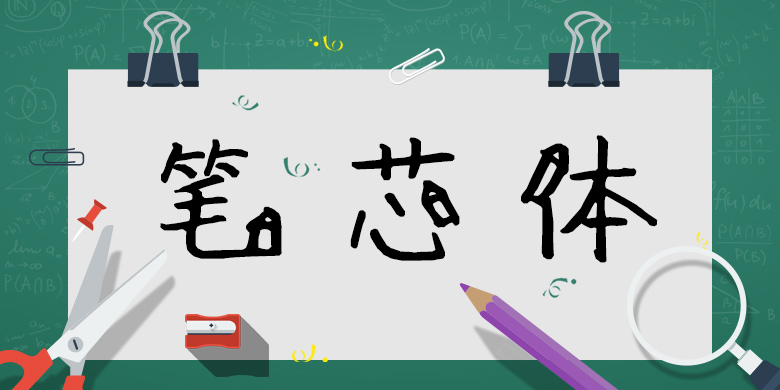
品牌:方正手迹设计师:赵维宁发行时间:2017字库编码:大陆简体(GB2312-80)分类:创意书写字体属性:精品字
笔芯体,简单温暖的字形搭配着双钩的铅笔造型元素,再辅以自然质朴的线条,让人感觉天真烂漫,充满着小孩子的纯真的稚气,趣味十足。适用于少年儿童类书籍、综艺字幕、品牌广告和产品包装设计,以及社交网络的个性化用字。